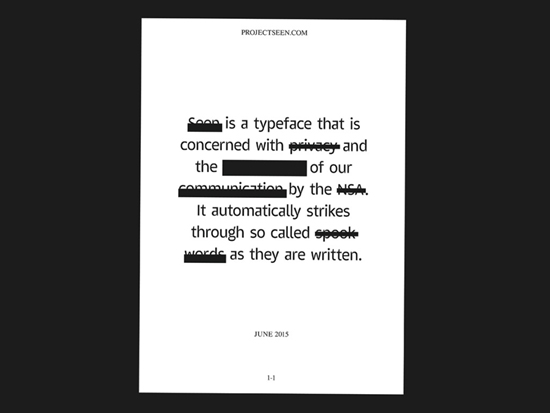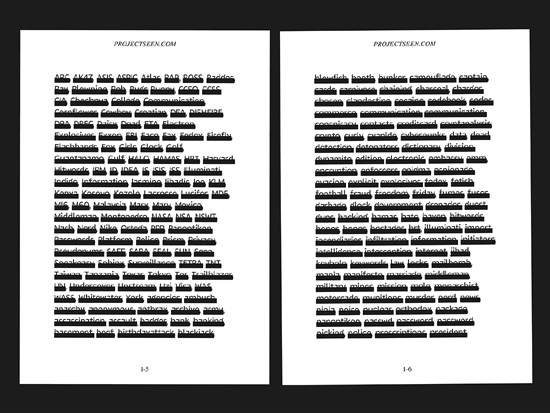
Шрифт, демонстрирующий, какие слова особенно волнуют спецслужбы США
Если Эдвард Сноуден чему-то и научил нас, так это тому, что правительство всегда следит за нами, внимательно слушает нас и читает то, что мы пишем. Ничто не ускользает от внимания спецслужб, которые неустанно следят за тем, чем занимаются граждане. В наше время под прицел попадают социальные сети, личная переписка, SMS-сообщения и многие другие способы общения между людьми. Дизайнер из Словении создал шрифт, который наглядно демонстрирует, какие конкретно слова попадают под пристальное внимание американских специальных агентов в первую очередь.
В Министерстве внутренней безопасности США есть список из 370 ключевых слов, которые постоянно отслеживаются в сети и телефонных разговорах. Список включает, как вполне очевидные «теги» вроде «Аль-Каида», «Северная Корея», «взрывник-самоубийца», так и непонятно как затесавшиеся туда слова «снег» и «помощь». Как только электронные программы слежения видят ключевое слово, их внимание тут же концентрируется на диалоге или обнаруженном в Сети материале.
Дизайнер Эмиль Козоле разработал загружаемый шрифт «Seen», который очень доходчиво демонстрирует, насколько легко попасть под пристальное внимание американских спецслужб. Ещё бы, попробуй написать рассказ или просто побеседовать с другом, не наступив на грабли «запрещённых слов». Как только вы пишете слово из вышеупомянутого списка, оно тут же зачёркивается жирной чёрной линией, такой же, какой обычно зачёркиваются важные имена и названия в секретных документах.
Дизайнер начал работать над своим шрифтом в 2013 году, сразу после того, как Эдвард Сноуден опубликовал разоблачающую АНБ информацию. К списку ключевых слов Министерства внутренней безопасности США Эмиль добавил также слова, которые отслеживают спецслужбы Великобритании, так как в то время он проходил обучение в одном из вузов Лондона. Получившийся шрифт в формате Adobe OpenType автоматически распознаёт эти слова и редактирует их.
Разумеется, этот шрифт не защитит вашу информацию от слежки, зато он является замечательной демонстрацией того, насколько трудно в наше время не привлечь к себе внимание разведки и силовых структур. Сам дизайнер говорит, что основная идея шрифта заключается в том, чтобы люди задумались над вопросом, почему вообще некоторые весьма безобидные слова попали в этот список. Скачать шрифт можно на официальном сайте.